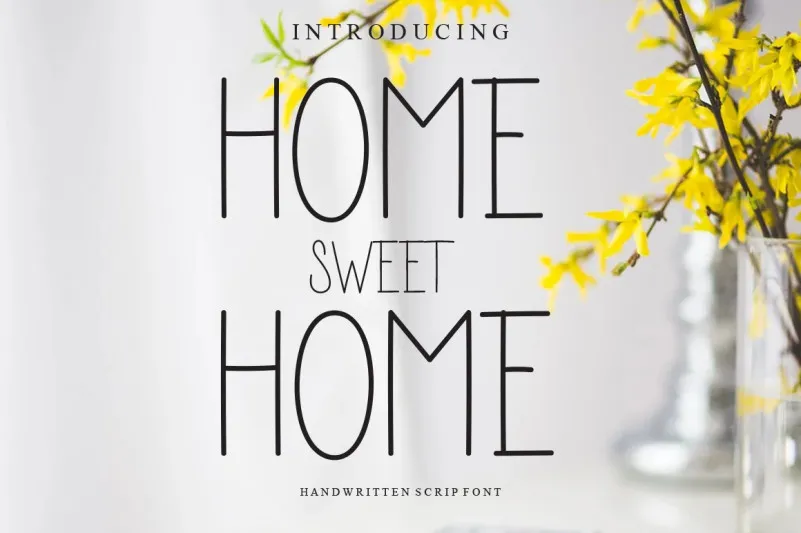
Esta é uma fonte frondosa, fina e adaptável escrita a mão. A qualquer assunto ou projeto que você escolha, essa font pode transformar sua coleção de fonts em algo extraordinário, potencialmente elevando qualquer criação. Perfeita para quem busca um estilo elegante e delicado, esta font oferece uma variedade infinita de aplicabilidades. Seja para marcas, títulos ou até mesmo textos interiores, ela irá deixar seu design mais sofisticado e atraente. Para designers em qualquer fase do processo criativo, este é um amigo valioso na sua biblioteca de fonts.